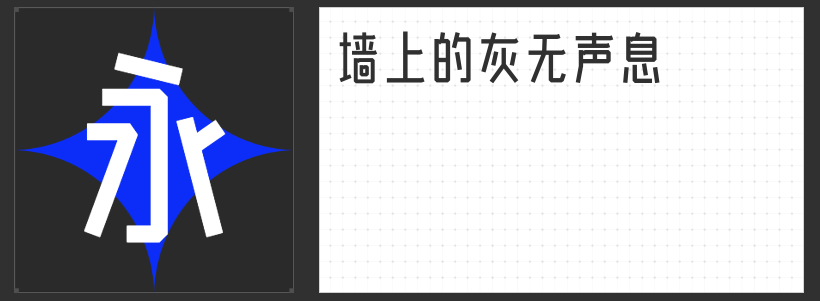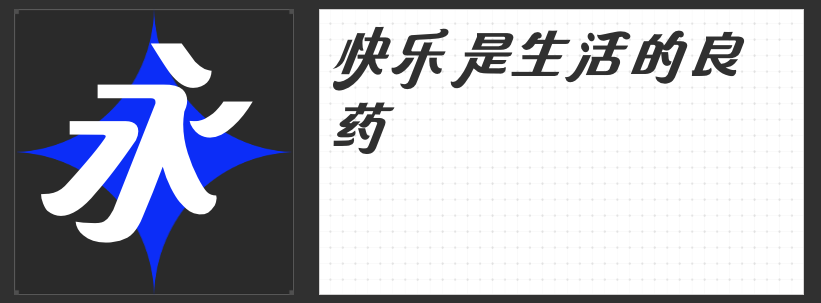
媒体设计中的字体美学:四款风格化字库解锁视觉叙事新维度
在媒体设计的视觉语言体系中,字体不仅是信息传递的载体,更是风格塑造与情感表达的核心工具。以下四款专业字库字体,以独特的设计逻辑与美学表达,为海报、广告、包装等场景提供差异化解决方案,助力设计师构建具有记忆点的视觉叙事。
一、造字侠伏魔简繁 传神
这款字体以“笔墨浓烈”为第一视觉特征,通过粗细对比强烈的笔画构建视觉张力。其核心设计亮点在于对“勾、提、挑、捺”等笔画的夸张处理——这些笔画以锐利的转折或延展的弧度突破传统结构框架,形成如书法飞白般的动态感。单字结构收放自如,既保留汉字中正的骨架,又通过局部笔画的延展打破呆板,使整体呈现出“静中有动”的矛盾美学。在需要强化视觉冲击力的标题设计中,其浓重的笔触与夸张的细节能瞬间抓住观者注意力。
二、造字侠郝刚快乐简 微黑
该字体以112度倾斜打破汉字横平竖直的视觉惯性,将西文斜体的优雅浪漫与汉字隶书的“蚕头燕尾”巧妙糅合。设计通过撇捺笔画的错落变化构建斜体的内在韵律,既保留隶书古朴的波磔特征,又以倾斜角度赋予现代感。微妙的平衡感体现在笔画粗细的过渡与空间布局中——既避免过度倾斜导致的视觉失衡,又通过笔画起收的细节处理强化节奏感。这种中西合璧的设计语言,使其成为时尚品牌、文化类媒体设计的优选。
三、励字玉树临风简
以“瘦长端正”为形态基准,这款字体通过修长的字形与朴拙的笔画传递东方美学中的“敛静”气质。其设计摒弃繁复装饰,以简洁的线条勾勒字形,却在细节处暗藏巧思:笔画转折处的微妙弧度、横竖画比例的精准把控,使字体在朴实中见精致。这种“拙中见巧”的风格,既能胜任正文标题的清晰传达,又可通过大小对比营造版面层次感,尤其适合需要传递文化底蕴的媒体场景。
四、励字山中精灵简
以“童稚趣味”为核心设计理念,这款字体通过拙朴的线条与均匀的布白构建可爱气质。笔画设计打破常规书写逻辑,以圆润的转折与夸张的部件比例强化趣味性,同时保持汉字的基本辨识度。其现代装饰趣味体现在对笔画细节的精心处理——既保留手写感的自然随性,又通过标准化设计确保视觉统一性。这种独特的风格使其在二次元内容、儿童品牌等年轻化媒体语境中具有天然亲和力。
从力量感书法到中西融合斜体,从东方禅意到童趣美学,这四款字体以差异化设计语言拓展了媒体设计的视觉边界。它们不仅满足基础的信息传达需求,更通过风格化的表达为作品注入情感温度,帮助设计师在信息过载的时代构建具有辨识度的视觉叙事。